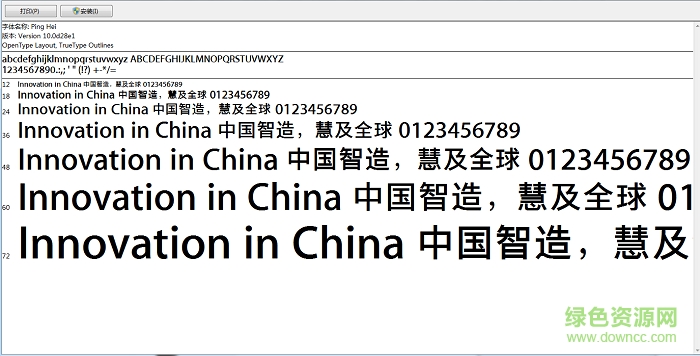
pinghei semibold字體
pinghei semibold字體是一款較粗的平黑字體,該字體有著具有清晰的結(jié)構(gòu)和流暢干凈的筆畫,外形設(shè)計(jì)精細(xì),線條粗可以用作文章標(biāo)題,屬于無襯線字體類,小伙伴們快來下載吧!
pinghei semibold字體